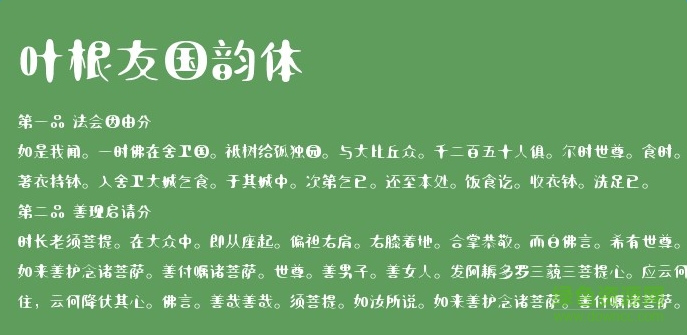
葉根友國(guó)韻體字體
葉根友國(guó)韻體是一款古典圓滑風(fēng)格字體軟件,國(guó)韻體筆畫(huà)工整配上圓滑的外形,沒(méi)有一絲棱角,創(chuàng)意十足,整體效果比較輕松簡(jiǎn)約,深受廣大年輕人喜愛(ài),還有更多好看字體歡迎來(lái)綠色資源網(wǎng)下載體驗(yàn)!
葉根友國(guó)韻體是一款具有中國(guó)東方韻味的漢字風(fēng)格字體,采用一種圓韻的風(fēng)格設(shè)計(jì),剛毅中去體會(huì)一種圓的精神融入中國(guó)漢字中,值得體會(huì)。